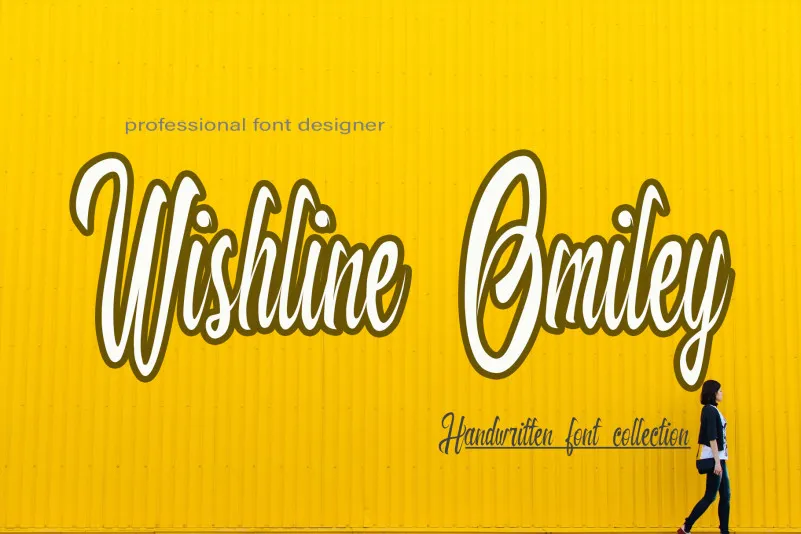
Wishline Omiley Font
A fonte ‘Wishline Omiley’ é uma elegante escolha para quem busca trazer a letra à vida em suas criações digitais. Esta moderna e divertida fonte escrita à mão é perfeita para dar mais vida aos seus projetos, tornando-os ainda mais reais e criativos. Ideal para estilos de design que buscam uma abordagem enérgica e alegre, ‘Wishline Omiley’ será sua aliada quando desejar adicionar um toque único à suas mensagens ou designs. Seja em cartazes, anúncios online ou designs gráficos, esse é o tipo de fonte que vai destacar seu trabalho, tornando-o ainda mais especial e emocionante para os olhos do público. Sua simplicidade única a torna uma ótima opção para designers e profissionais digitais buscarem um gás novo em seus trabalhos criativos.